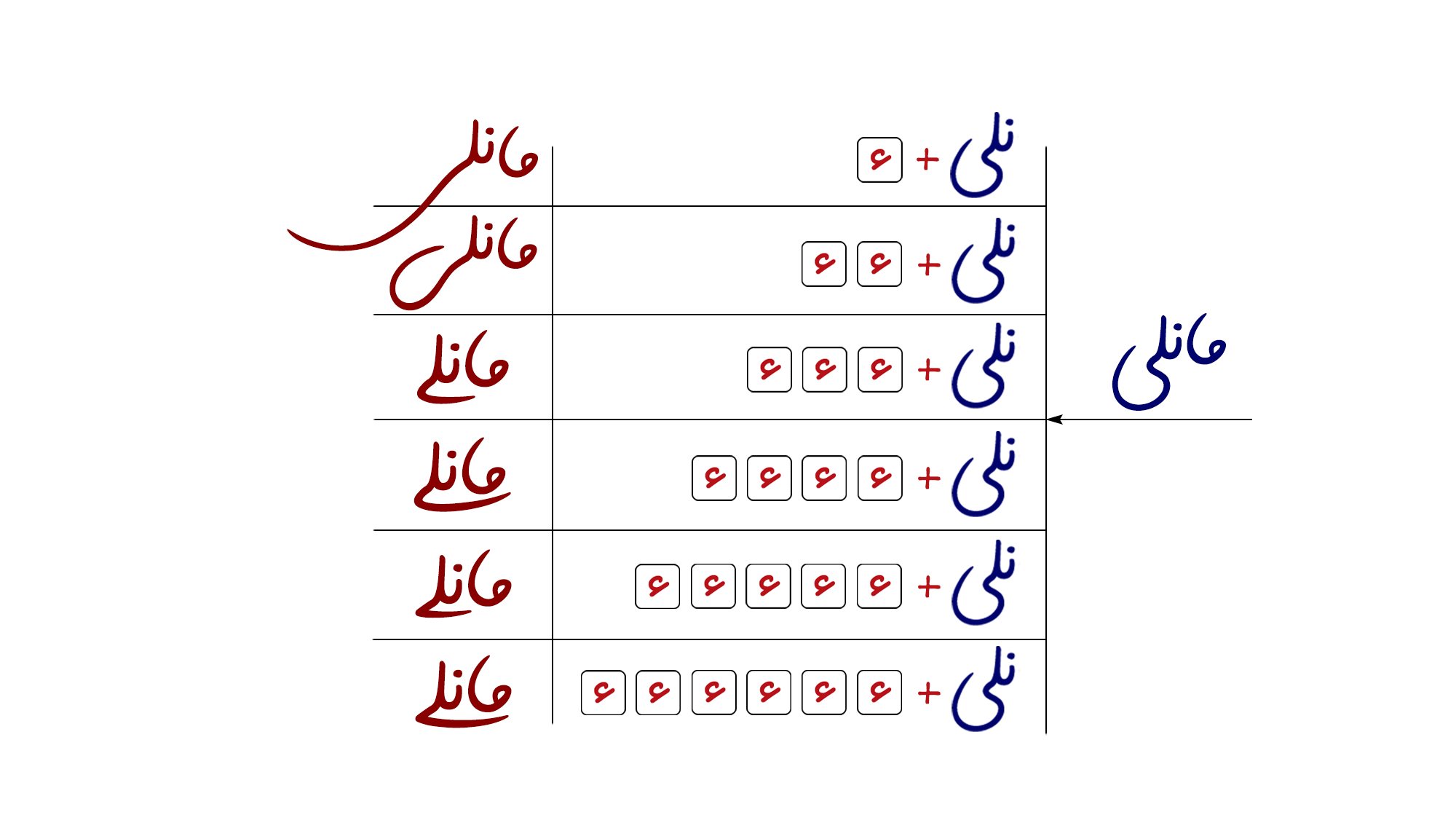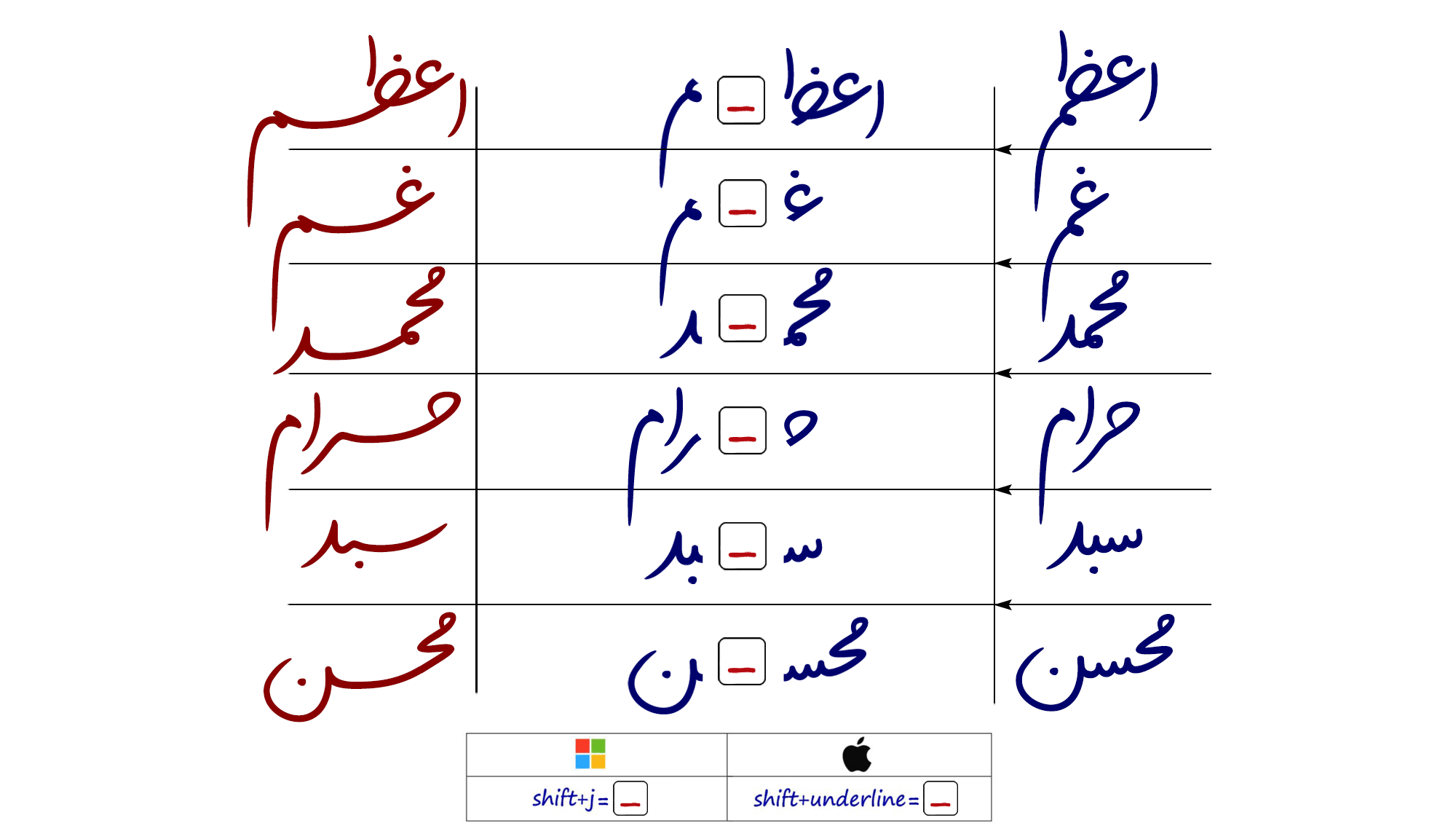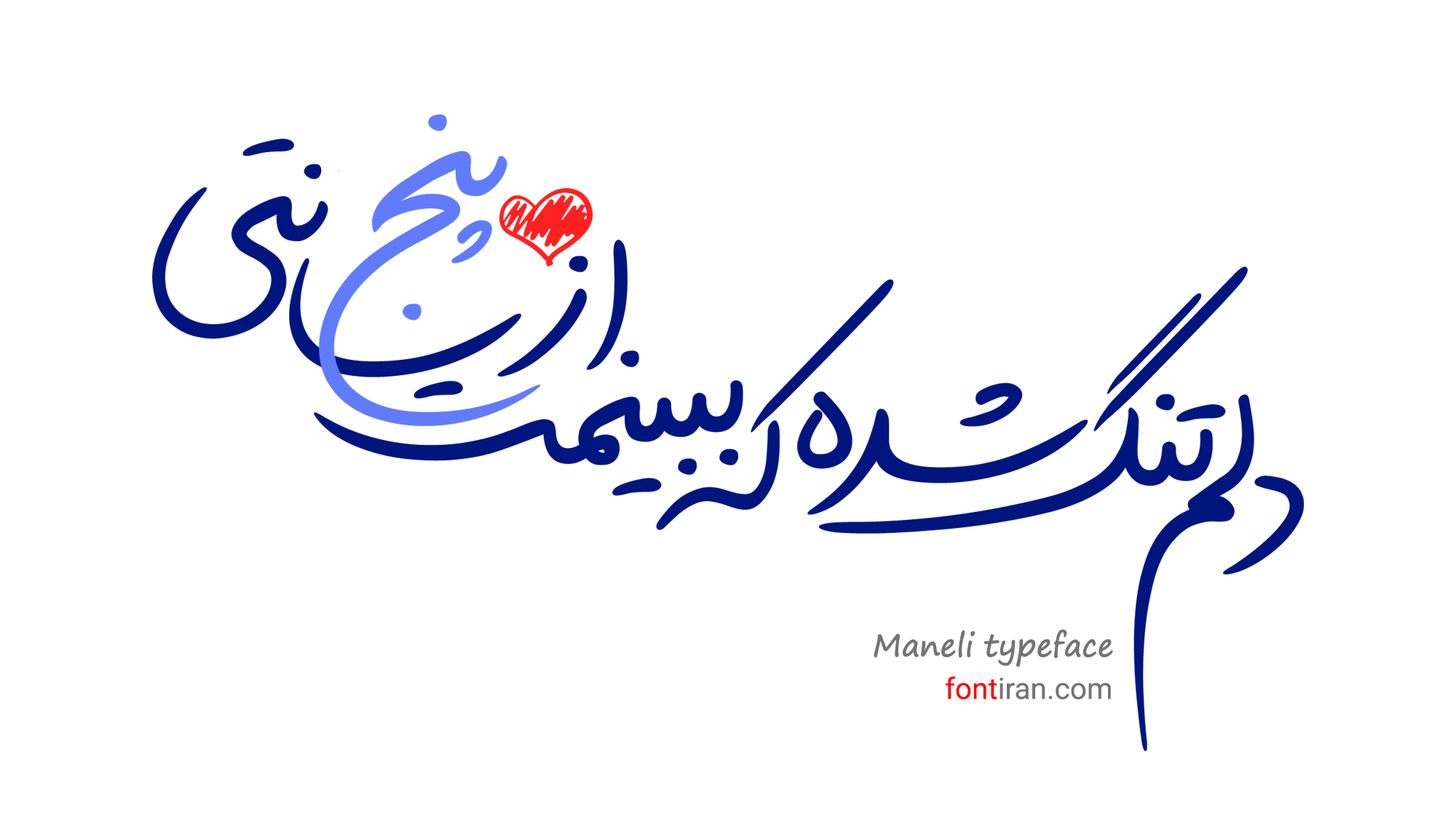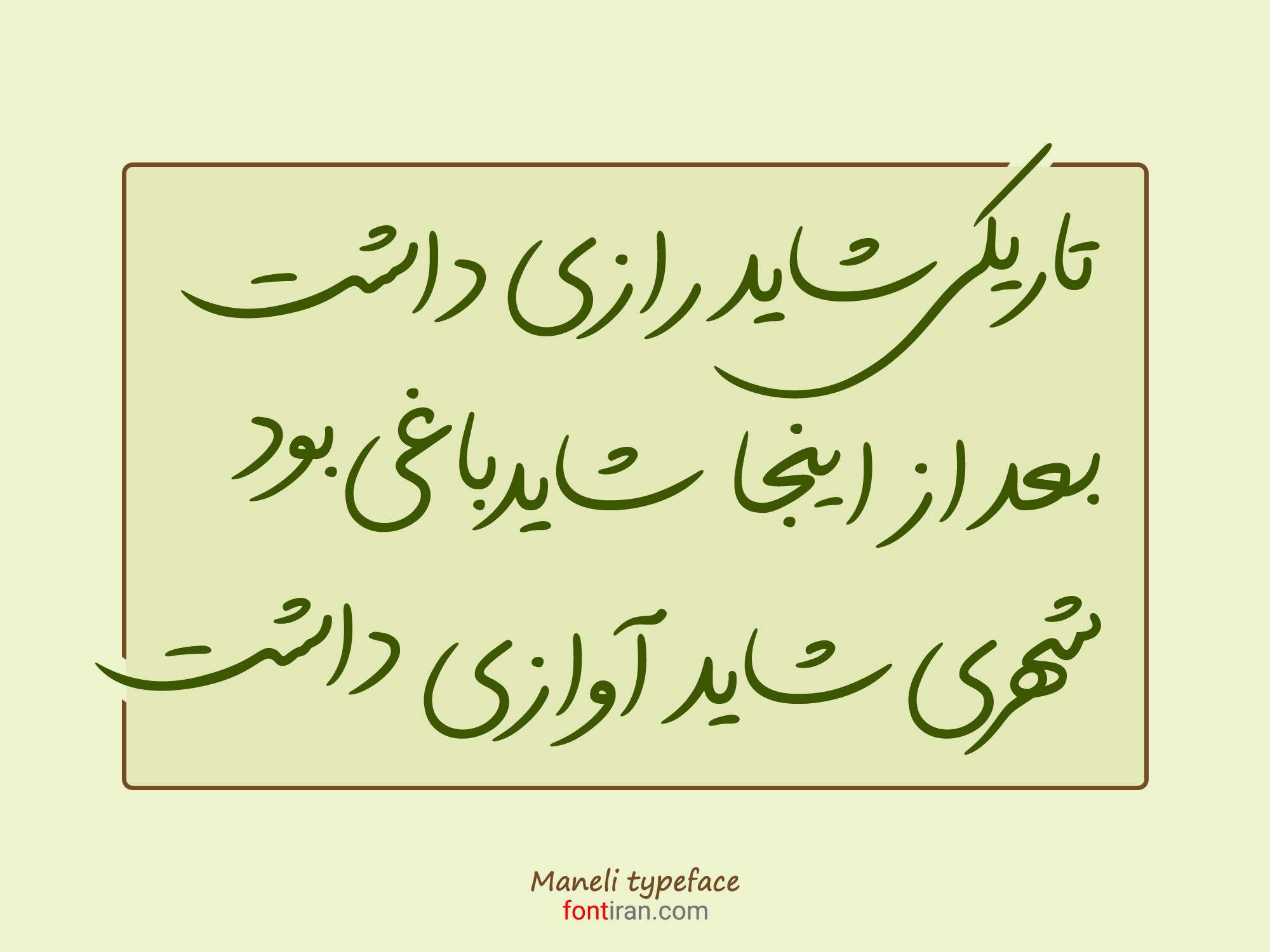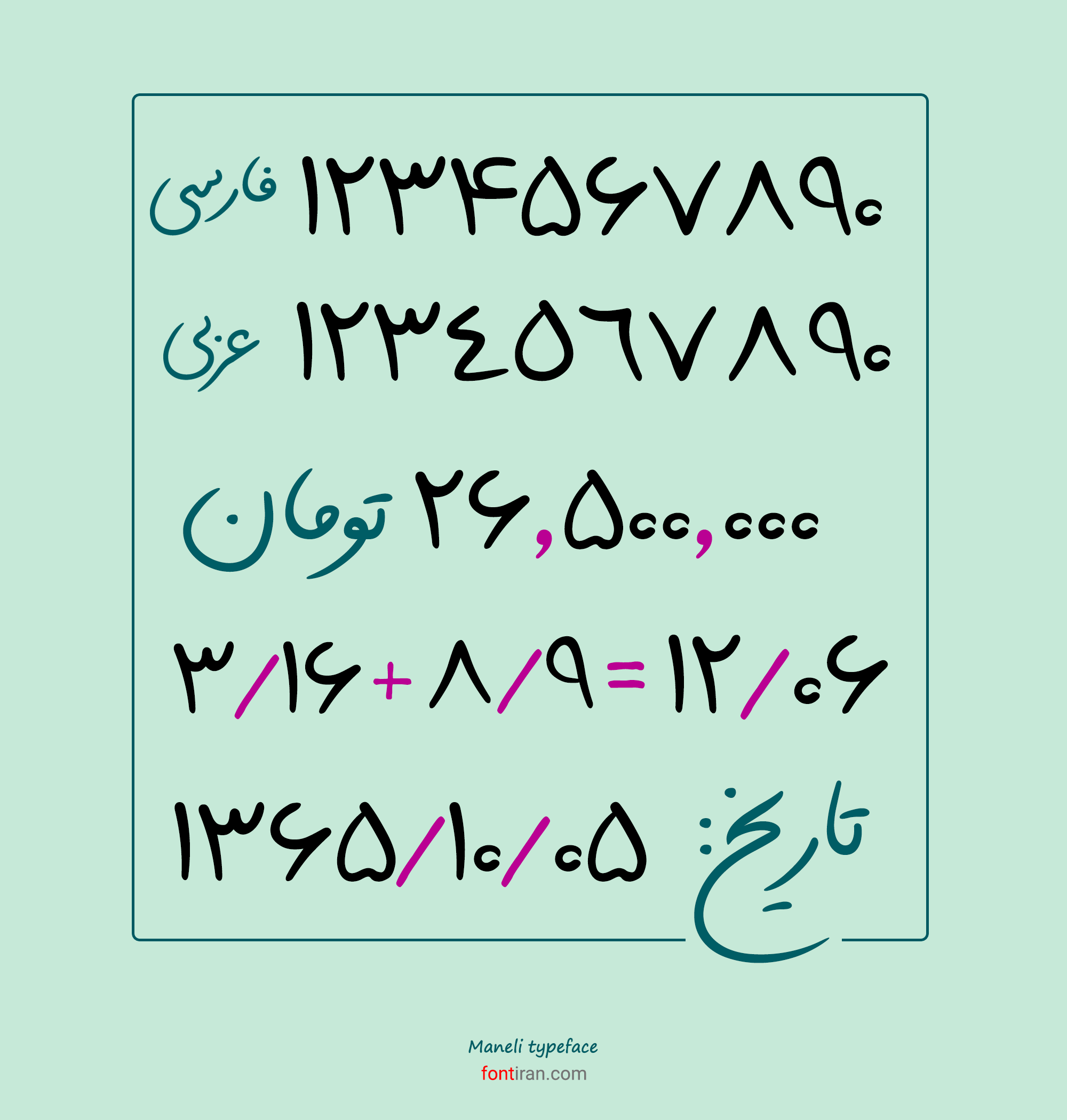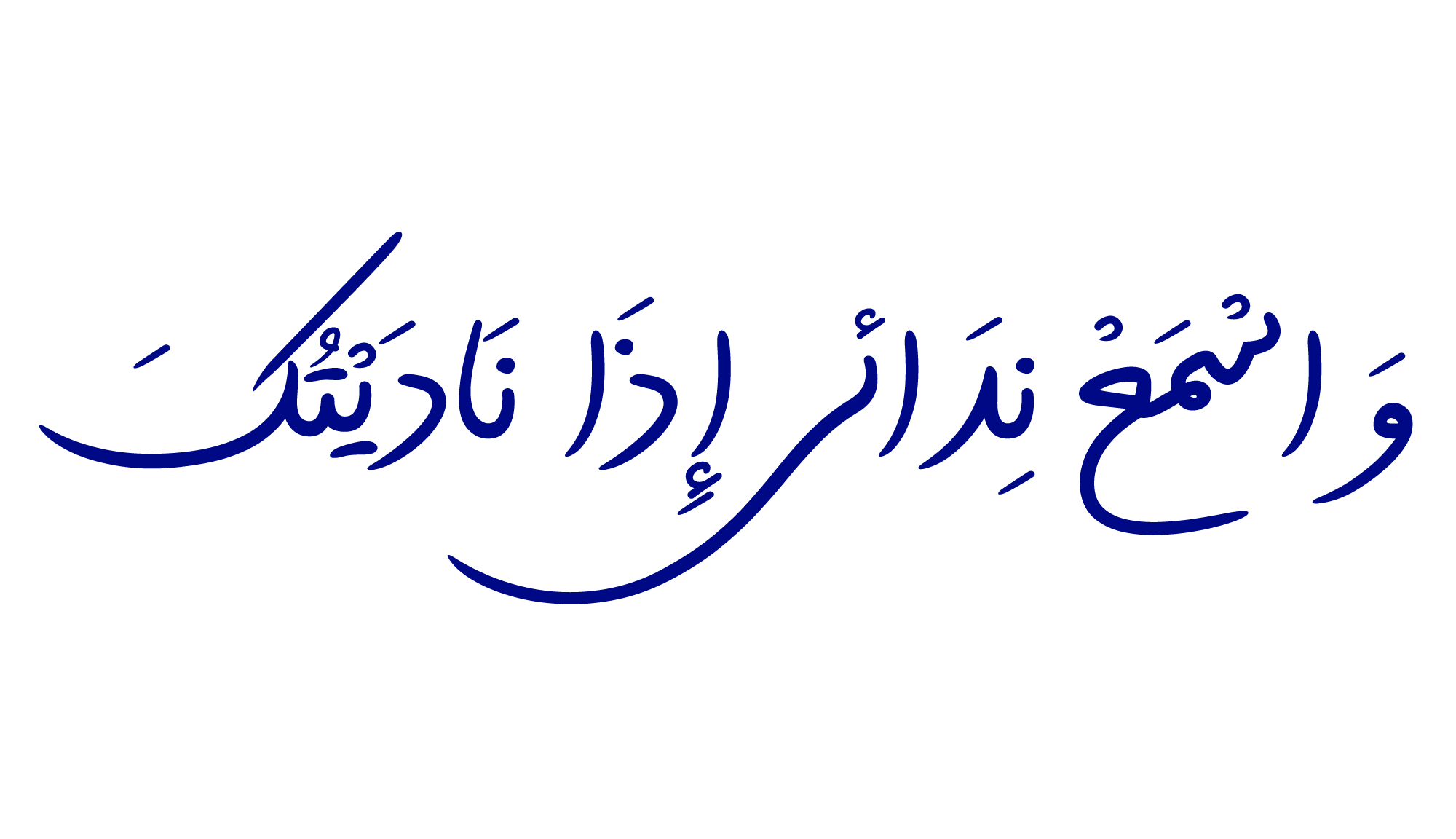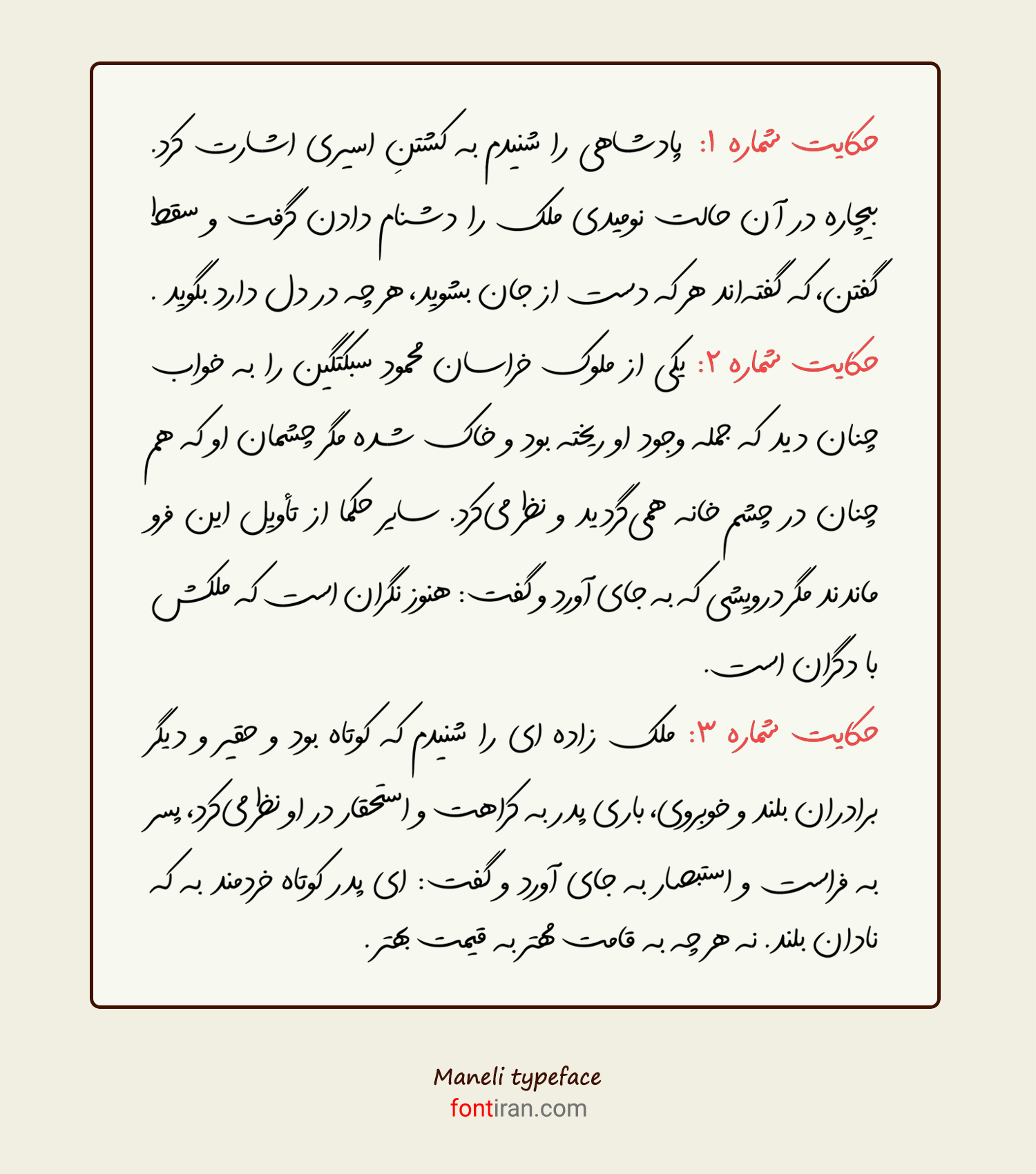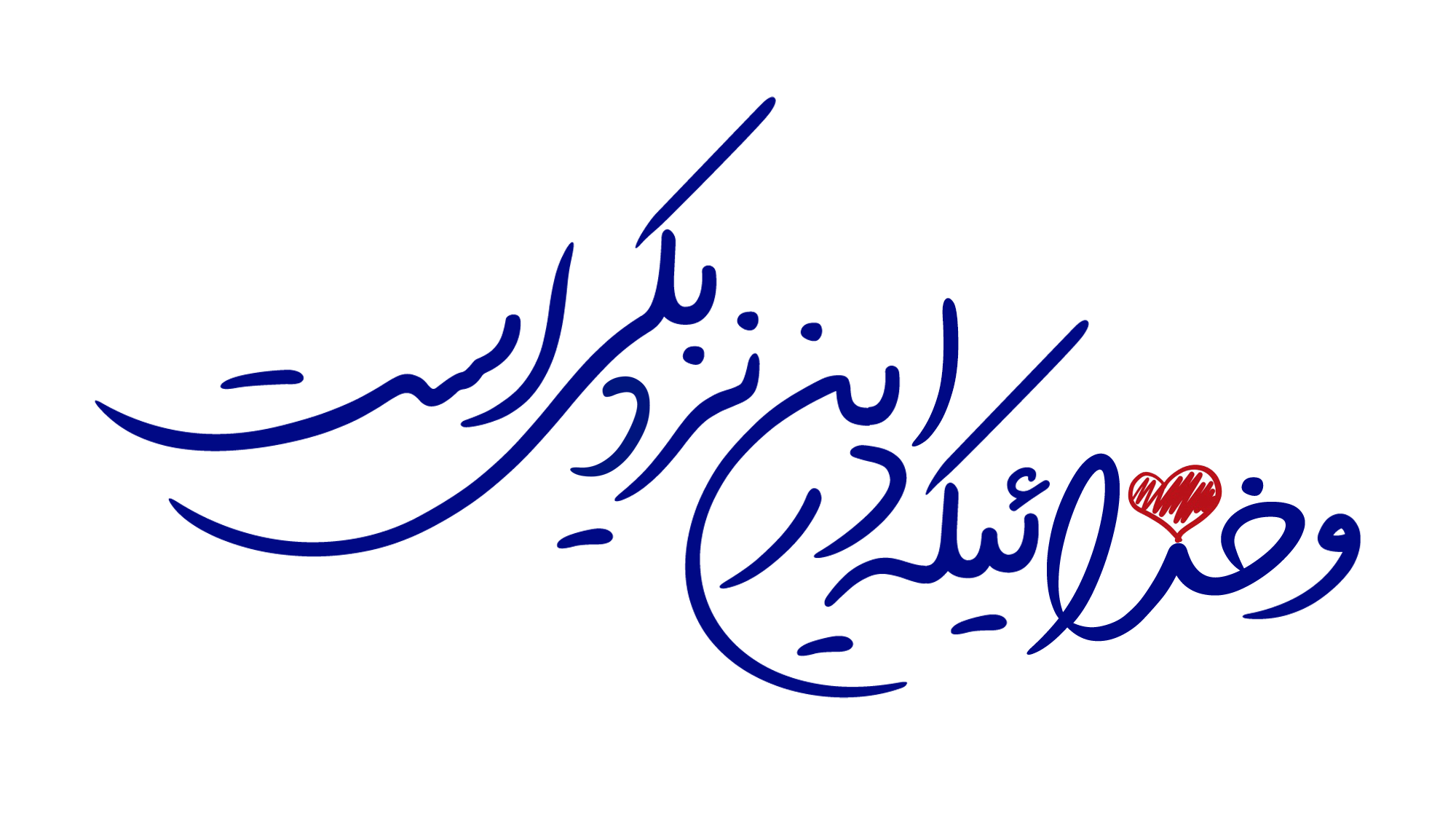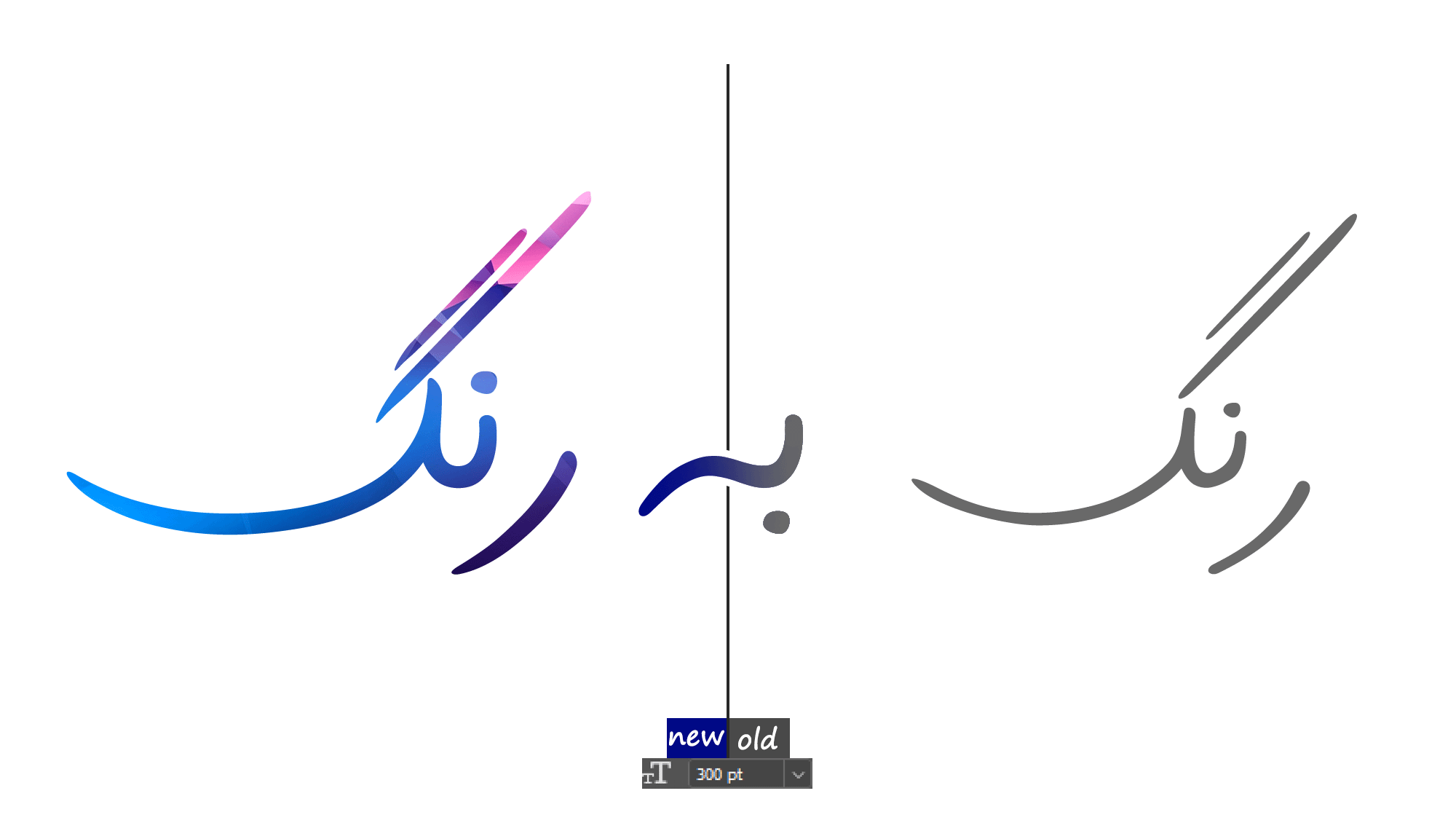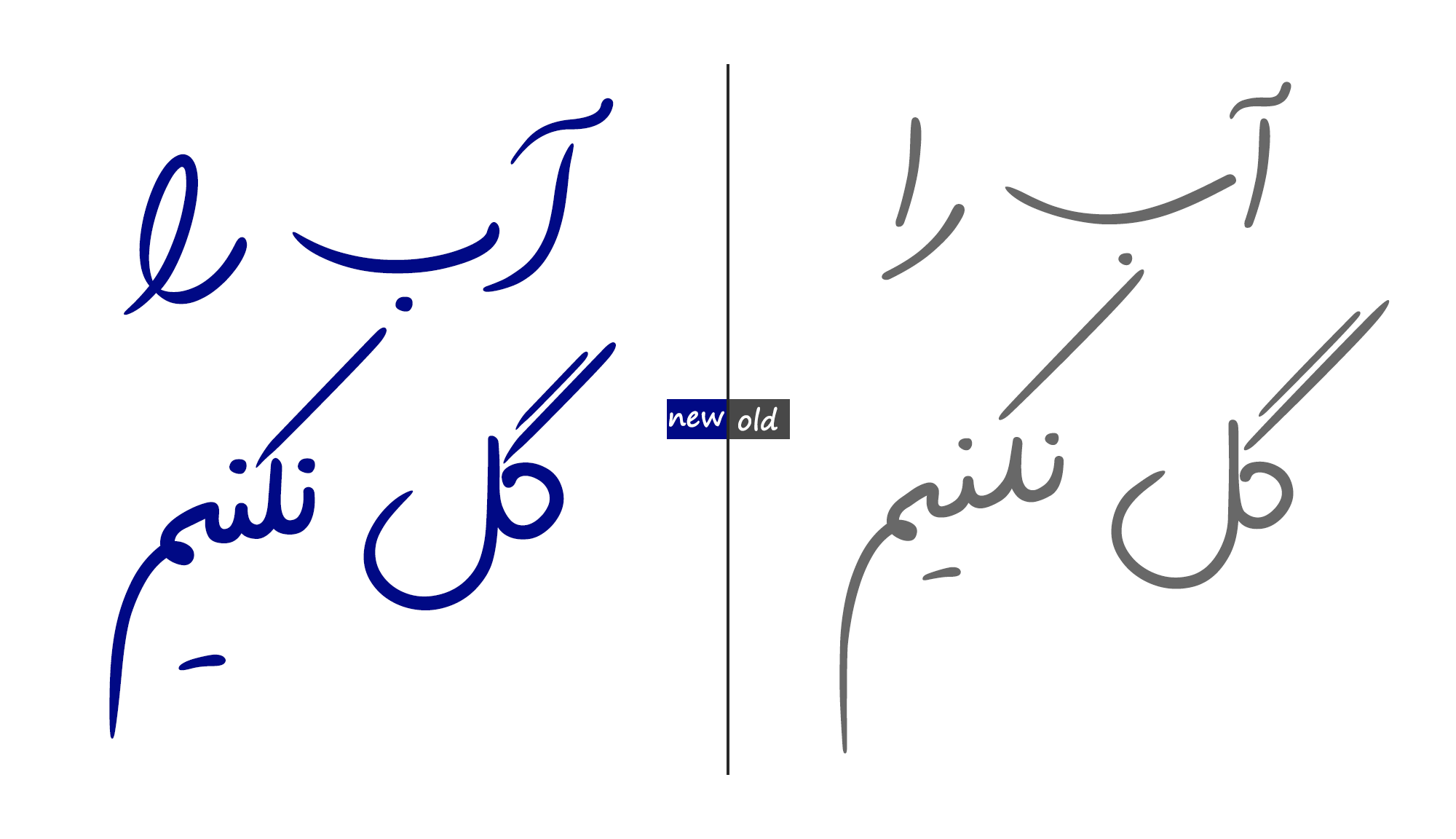
حروف جایگزین در فونت مانلی
در نسخه جدید فونت مانلی حروف و ترکیبات جایگزین متنوعی وجود دارد. همراه با فونت یک فایل راهنما دریافت میکنید که با مشاهده آن خواهید دانست کدام حروف را میتوان تغییر داد.
در اینجا یک مثال از راهنمای نحوه تایپ حرف جایگزین “ی” را میتوانید ببینید.
کشیده در فونت مانلی
اعداد و علایم در فونت مانلی
اعراب گذاری در فونت مانلی ۲
نمونه نوشته خام (متن) از فونت مانلی
مقایسه با نسخه قدیمی فونت مانلی
مقایسه با فونت دست نویس لیلا
- یه امکان باحال در فونت مانلی اینه که میتونید اشتباهات تایپیتون رو بجای پاک کردن خط بزنید!